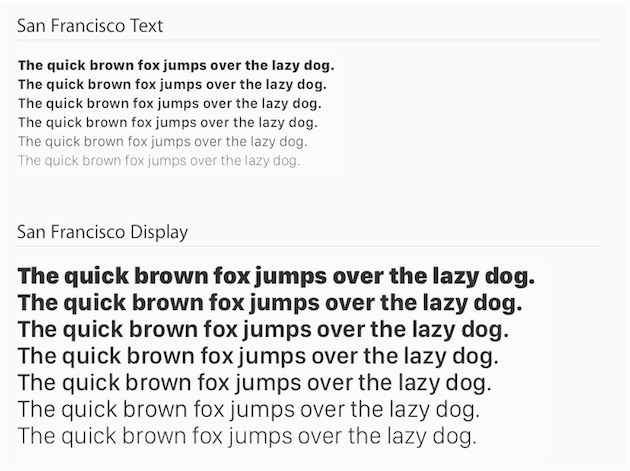
Apple ha rilasciato il font di sistema “San Francisco” agli sviluppatori che lavorano su iOS 9, OS X El Capitan e watchOS 2. Il font in questione usato usato anche da iOS 9 e il nuovo OS X, progettato per essere facilmente leggibile sugli schermi.
Come ampiamente previsto, con OS X 10.11 “El Capitan” Apple ha adottato un nuovo font di sistema denominato San Francisco e già visto su Apple Watch. In realtà il font del nuovo sistema non è esattamente lo stesso che Apple ha usato sullo smartwatch ma una variante specifica per gli schermi più grandei I font “San Francisco” che ha creato Apple sono due: “San Francisco Display” e “San Francisco Text”. La larghezza tra le lettere nella variante Display è minore, rispetto all’altra; la prima, infatti, è pensata per l’uso con schermi più grandi, l’altra per schermi più piccoli.